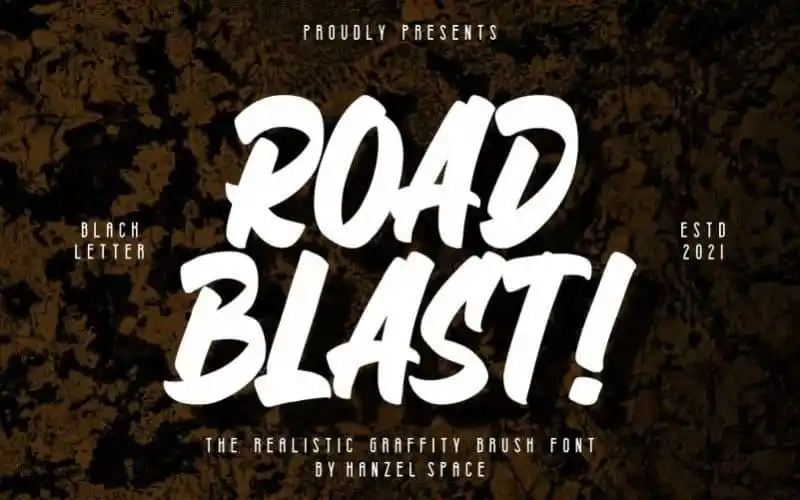
A Road Blast Brush Font é uma delicada fonte elaborada pela Hanzel Studio, perfeita para quem busca adicionar um toque nostálgico a seus projetos digitais. Ela se destaca por seu estilo versátil e incrivelmente dinâmico, especialmente quando combinada com letras escritas à mão. Perfeito para logos, cartões de mensagem, embalagens de produtos, cabeçalhos de postagem, materiais publicitários, slogans e cartazes, esta fonte oferece uma sensação de viagem no tempo, ideal para projetos que buscam um aspecto retro e encantador. Não perca essa oportunidade de tornar seus designs únicos com a Road Blast Brush Font, disponível nas categorias de Script Fonts.